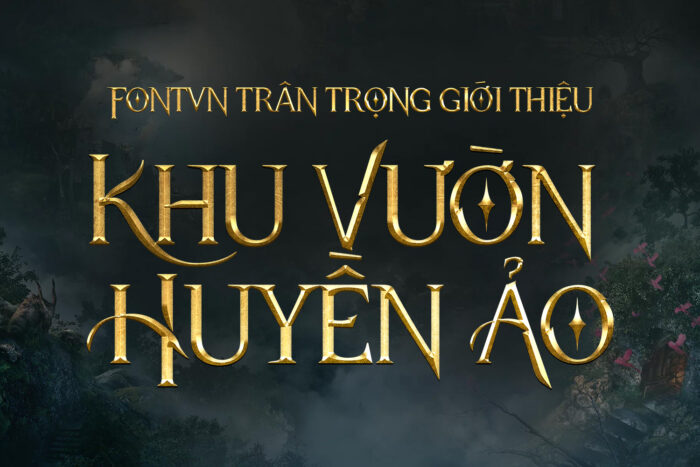
DVN Hogwarts Việt hóa – Font chữ Gaming, Harry Potter cực đỉnh
DVN Hogwarts là một font chữ mang đậm phong cách thần bí và cổ điển, lấy cảm hứng từ thế giới phù thủy của Harry Potter. Được Việt hóa cẩn thận để đáp ứng nhu cầu người dùng trong nước, font chữ này giữ nguyên nét thanh thoát, ma mị của phiên bản gốc nhưng lại được điều chỉnh khéo léo để phù hợp với các ký tự tiếng Việt.
Với phong cách chữ Gothic kết hợp những nét tròn, mạnh mẽ và đầy ấn tượng, DVN Hogwarts hoàn toàn thích hợp cho các dự án game, banner quảng cáo, hoặc các sản phẩm liên quan đến thế giới kỳ ảo. Kiểu chữ này đặc biệt phù hợp cho các tựa game nhập vai, hành động, hay các dự án liên quan đến phim ảnh và giải trí.
Không chỉ đẹp mắt, font DVN Hogwarts còn giúp tạo cảm giác quyền lực và kỳ diệu, mang lại sự chuyên nghiệp trong mọi thiết kế.